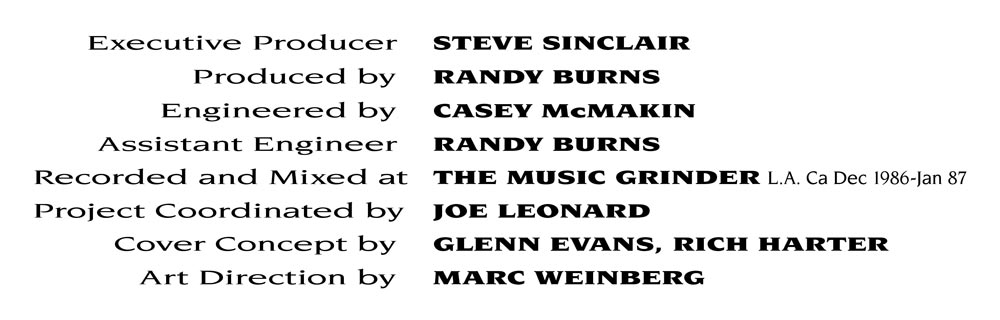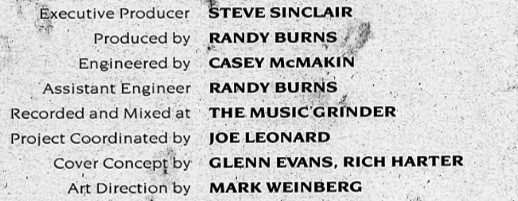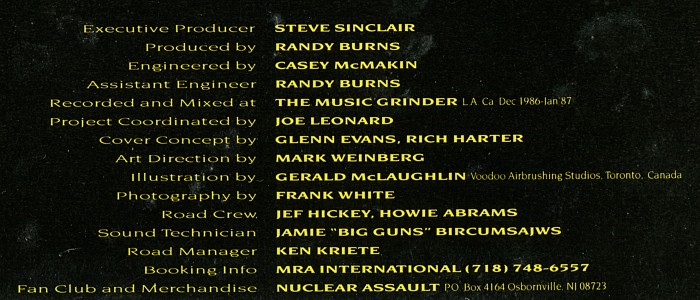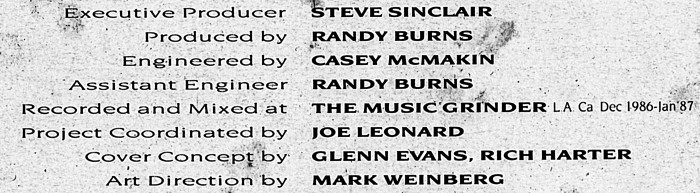
Schrift für Vinylveröffentlichung
ich suche für eine Vinyl-Veröffentlichung, die dem Original sehr nahe kommen muß, eine Schrift. Ich dachte erst, es wäre die Optima, die extrem verbreitert wurde. Leider ist sie das nicht. Kann mir jemand anhand des Textbeispieles helfen?
hier ein nachgeschärftes Beispiel
die Auflösung ist viel zu gering um die Schrift auch nur annähernd sicher identifizieren zu können. In die Richtung gehen Schriften wie Strayhorn MT (müsste man aber breitziehen) und Minerva Modern (die Spitzen vom A, M, N passen nicht, das gilt auch für anderen Schriften wie die Optima).
Die Strayhorn und Minerva habe ich mir angeschaut, die kommen vom Schriftcharakter schon nahe. Wahrscheinlich werde ich mich mit einem Kompromiß anfreunden müssen.
Ich habe eben mal Discogs mit den Daten gefüttert: Ist es die „The Plague“?
Dann wäre das Erscheinungsjahr des Originals 1987 und damit könnte man die Ergebnisse vielleicht schon mal etwas eingrenzen.
Richtig, es ist Nuclear Assault - The Plague von 87.
Muß in den Credits ein paar Namen tauschen und will eben so nah wie möglich am Original bleiben. Finde aber nur Fonts, die dieser hier ähnlich sind. Abweichungen sind leider immer wieder vorhanden.
Mir kommt die Schrift auch heftig in die Länge gezogen vor.
Ich hab das mal nach Gefühl entstreckt:
Das geht IMHO doch eindeutig Richtung Strayhorn ... Ein Blick in die Geschichte der Schrift und dann wird es interessant:
Strayhorn
A sans-serif adaptation of Ellington, and named after Duke Ellington's long-time jazz collaborator Billy Strayhorn.
Sogar der Kontext „Musik“ passt da? War das Cover Original oder eine Neuauflage aus der Zeit ab 1998? Bei einer Neuauflage wäre die Strayhorn durchaus möglich. Oder es gab eine u.U. unveröffentlichte Schrift viele Jahre vorher, welche dann die weitere Entwicklung entscheidend beeinflusst hat? Aber möglicherweise sind wir hier bereits weit genug gekommen und die Strayhorn kann als passend definiert werden.
Falls Du das Ganze neu setzen willst, könnten auch diese beiden von Stil her interessant sein:
Bei der Sweet Gothic gibt es allerdings keine »normalen« Kleinbuchstaben, scheint es.
vielen Dank für die Antworten. Die Novarese ist es !!!